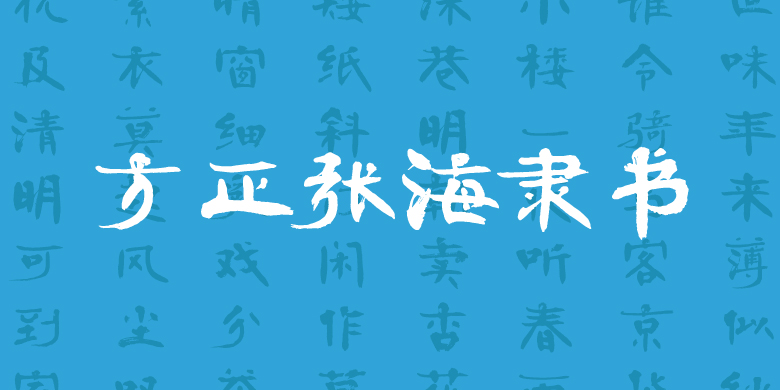
方正张海隶书
方正张海隶书,这款字体结构工整、笔画清晰,兼顾美观与易读性,适用于标题、正文、海报、包装、LOGO 等多种场景。字形优雅稳定,风格百搭耐看,适配日常排版与创意设计,让文字呈现更舒适、更具质感。方正张海隶书一笔一画,皆是细节,以均衡的比例、流畅的线条打造舒适视觉体验,字形端正大气,风格简约现代。无论是商业设计、品牌宣传还是日常排版,都能轻松驾驭,让文字更有格调与力量。方正张海隶书字体下载。
作为一名书法工作者,服务人民回报社会,既是时代赋予的使命,也是应尽的职业担当。中国书法家协会名誉主席张海先生今年已经八十二岁,应北大方正字库团队之约,以及社会的客观需要,用半年时间,以自己擅长的“草隶”书写了8000多个常用单字。所谓“草隶”,即以汉隶为本,融入汉简、草书的笔意,形成的独特艺术风格,被业内人士广泛认同。经过工作人员辛勤努力,建成代号为“FZZhangHLSJF”的书法字库,安装操作之后,便能轻松转化出“书法作品”。从标准字库到个性化字库,反映了人们审美多样化的需求,证明了内心深处的书法情结。正因如此,您在键盘或屏幕输入标准化字符之余,能偶然邂逅该字库,选择并输出一行,也许能唤醒一丝半缕对书法的遐想,足矣。